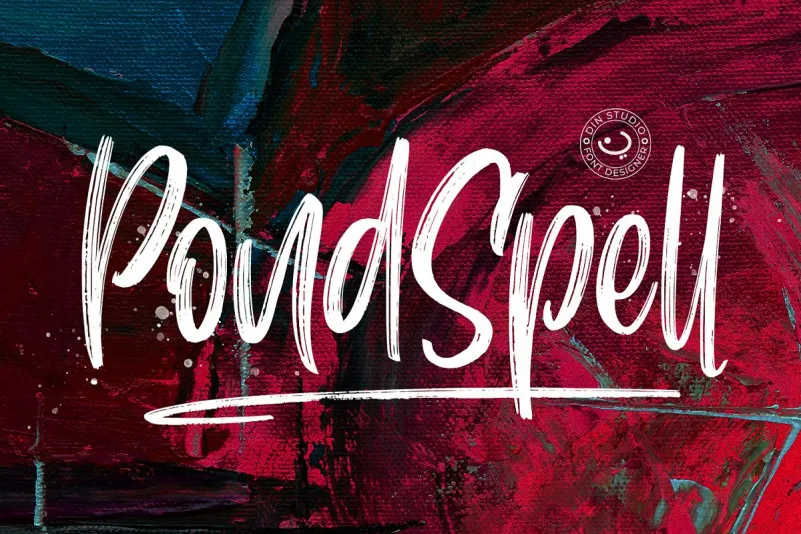
Pondspell Brush Font – Download Grátis
Descubra a elegância natural e a sofisticação que a Pondspell Brush Font pode trazer para seus projetos design. Esta fonte está categorizada como Script Fonts e é uma criação cuidadosamente meticulosa do designer Din Studio, disponível na categoria 0001themes. Com sua textura feita de um pincel natural, essa fonte traz uma atmosfera única que combina a simplicidade da caneta com o charme dos desenhos à mão livre. Pondspell Brush Font é perfeita para design de marca, frases, títulos de livros e muito mais. Seu aspecto desajeitado e rico em texturas é resultado do uso de uma simples ferramenta de pincel, mas seu impacto na estética final é inegável, tornando qualquer projeto ainda mais autêntico e poderoso. Este é o tipo de fonte que você pode incorporar com facilidade em projetos variados sem preocupações excessivas, garantindo um resultado atraente e original. A Pondspell Brush Font oferece uma maneira natural de dar vida aos seus designs, elevando-os a um novo nível de sofisticação.